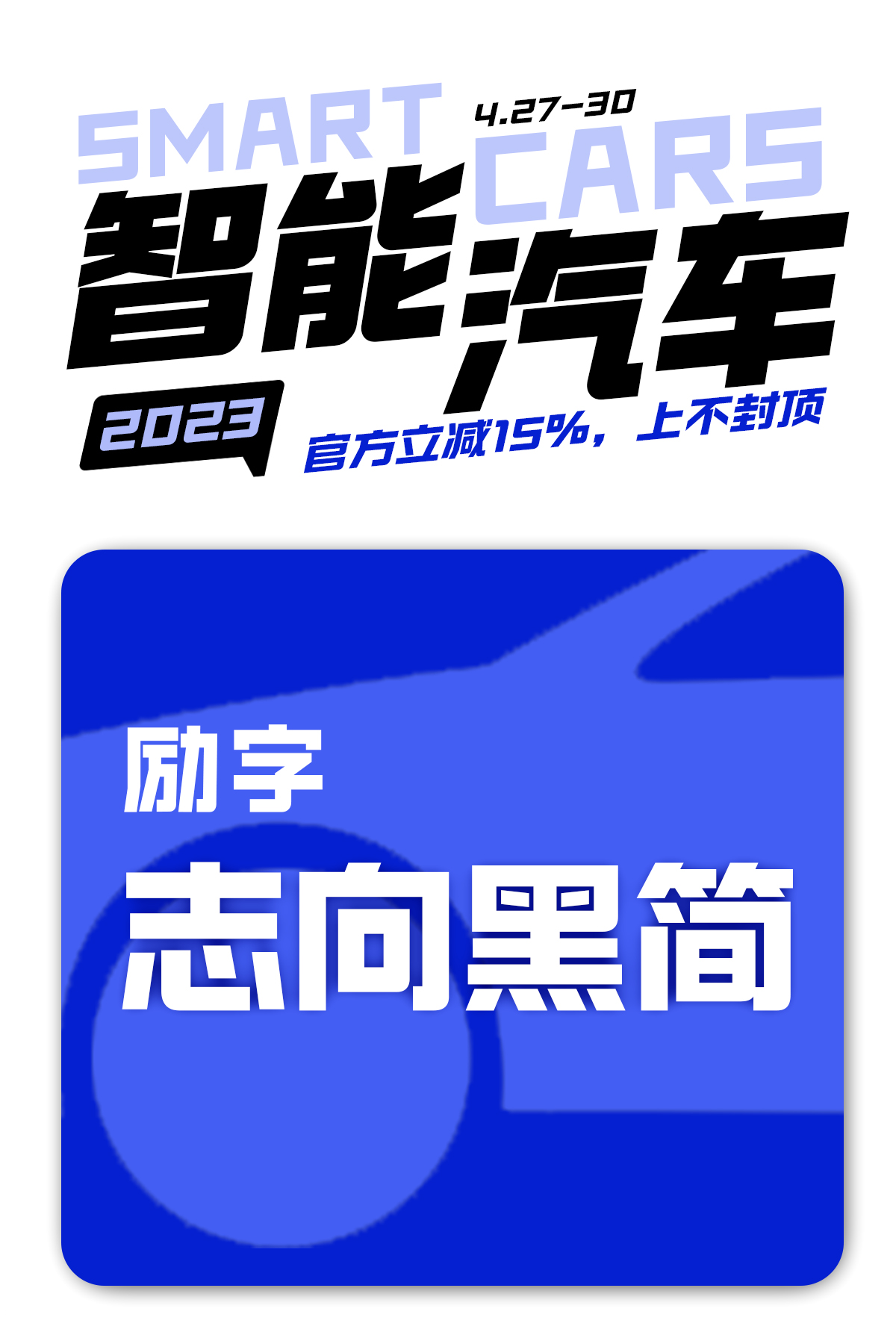
一款满满正能量的励志字体——励字志向黑简
嘈杂严苛的网络环境让各品牌都风声鹤唳,蹭热点、买流量、博眼球各种奇招百出的营销动作让消费者应接不暇,AI智能的进步,使市场更多选择,如何厘清重点,进行符合品牌调性的输出呢?
今天励字造梦局推出一款励志正能量的字体——励字志向黑简,采用圆体与黑体的融合,在笔画拐角增加适当的外圆角的手法在整体稳重大气的字形中增添少许灵动,使字体字面充实,结构稳定之余,更适配屏显的使用。